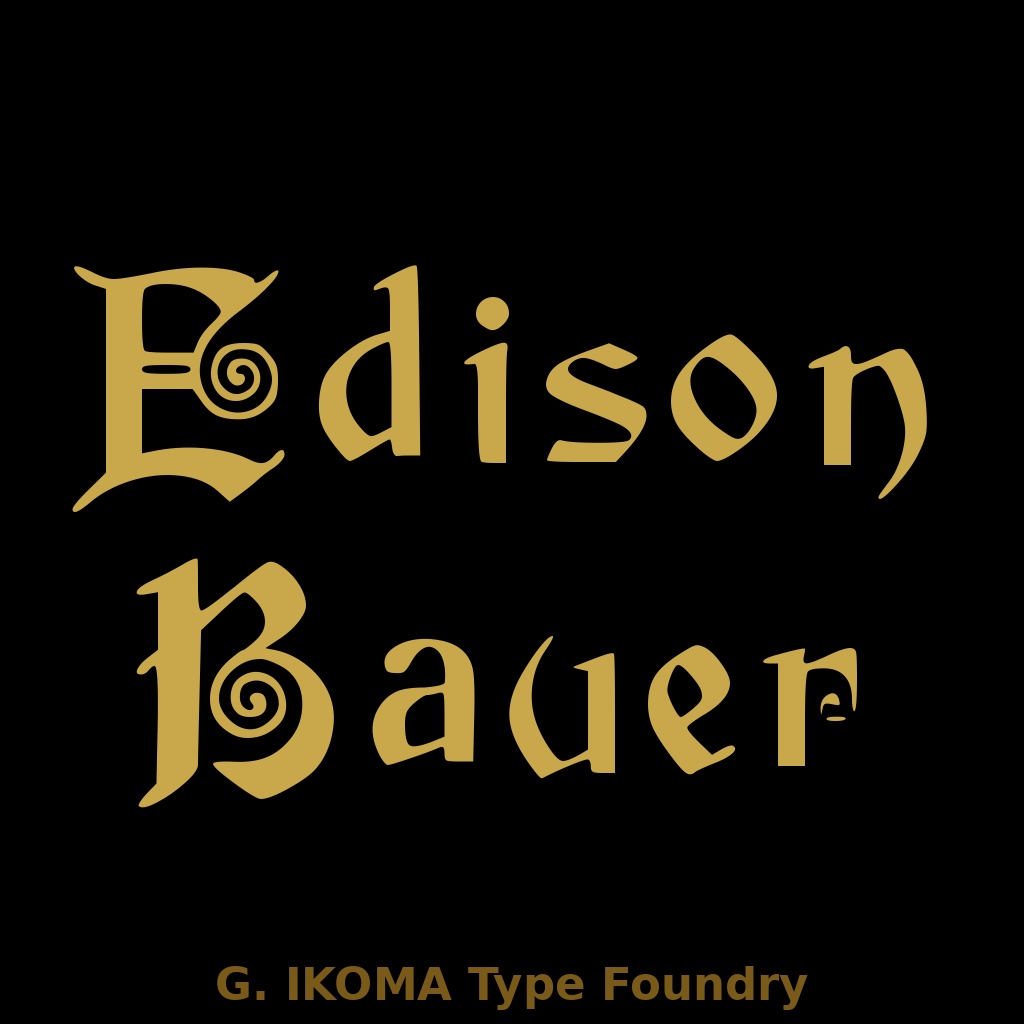
Edison Bauer — 19世紀欧州印刷資料復元フォント / Historical Revival Typeface [Jugendstil Blackletter]
━━━━━━━━━━━━━━━━━━━━━━━━━ 【フォントについて】 ━━━━━━━━━━━━━━━━━━━━━━━━━ Olympian Stephenson Extended は、19世紀末〜20世紀初頭の欧州印刷資料を原典に、手作業でトレース・デジタル化した復元フォントです。 本作は、Stephenson, Blake & Co., London による Victorian Display Serif をもとに再構成したものです。 原典資料には「Moment, Commode, Stock / RELIGION.CHARLOTTE」と記されています。 重厚なセリフと装飾的なレタリングが特徴のヴィクトリア朝風ディスプレイ書体です。 デジタル化にあたり、原典の基本文字に加えて各種記号を追加収録しており("Extended"の由来)、欧州言語でのデザイン用途にも対応した拡張グリフセットとなっています。 原典:Ludwig Petzendorfer, Schriften-Atlas 1898 (Neue Folge 1903) Julius Hoffmann, Stuttgart(パブリックドメイン) 様式:Victorian Display Serif 収録グリフ:134文字(A–Z / a–z / 0–9 / アクセント付き文字 / 記号類 / 中黒) 欠落グリフ:なし 制作:株式会社生駒時計店 / G. IKOMA, LTD.(1870年創業) ━━━━━━━━━━━━━━━━━━━━━━━━━ 【ご購入前にご確認ください】 ━━━━━━━━━━━━━━━━━━━━━━━━━ 本フォントは TTF 形式のみの提供です。利便性を優先して TTF を採用しているため、原典資料に収録されていた Œ(OEリガチャ)は含まれません。 Victorian Display Serif の特性上、装飾性を重視した設計です。 ロゴ・見出し・タイトルなど大きく使う用途に最適ですが、本文組版や小サイズでの長文には向きません。 また、原典由来の字形をもとに再構成しているため、現代的な汎用書体のような 設計ではありません。 ━━━━━━━━━━━━━━━━━━━━━━━━━ 【収録内容】 ━━━━━━━━━━━━━━━━━━━━━━━━━ ・I_Olympian_Stephenson_Extended.ttf ・LICENSE.txt(日英) ━━━━━━━━━━━━━━━━━━━━━━━━━ 【推奨用途】 ━━━━━━━━━━━━━━━━━━━━━━━━━ ・ロゴ・ブランド名 ・新聞・雑誌風レイアウトの見出し ・アンティーク・ヴィンテージ系パッケージデザイン ・ウイスキー・クラフトビール等のラベルデザイン ・映画・ゲームのタイトルロゴ(英国・歴史物) ・Tシャツ・グッズのプリントデザイン ・ポスター・フライヤーのタイトル 19世紀英国の格調と重厚感を演出するデザインに最適です。 本文組版や小サイズでの常用には向きません。 ━━━━━━━━━━━━━━━━━━━━━━━━━ 【ライセンス】 ━━━━━━━━━━━━━━━━━━━━━━━━━ 本フォントは、個人利用・商用利用を問わず、印刷物、画像、ロゴ、バナー、 動画サムネイル等の制作に使用できます。 また、WebサイトやSNSで画像化された状態で使用することは可能です。 ただし、以下の行為は禁止します。 ・フォントファイルそのものの再配布、再販売、譲渡、共有 ・改変したフォントファイルの配布 ・本フォントを素材集、テンプレート、デジタル商品等に収録して再販売する行為 ・本フォントファイルをWebフォントとしてサーバーに設置・配信して利用する行為 ・アプリケーション、ゲーム、ソフトウェア、電子機器等への埋め込み利用 ・AI学習、機械学習、生成モデル訓練等への利用 ・本フォント自体または収録字形そのものについて独占的権利を主張する行為 詳細は同梱の LICENSE.txt をご確認ください。 ━━━━━━━━━━━━━━━━━━━━━━━━━ 【原典資料について】 ━━━━━━━━━━━━━━━━━━━━━━━━━ 本フォントは、G. IKOMA, LTD. 所蔵の実物資料をもとに制作しています。 原典資料そのものは本商品に含まれていません。 資料アーカイブについては、下記サイトをご参照ください。 G. IKOMA Archive https://g-ikoma-archive.netlify.app/ ━━━━━━━━━━━━━━━━━━━━━━━━━ BOOTH: https://g-ikoma.booth.pm/